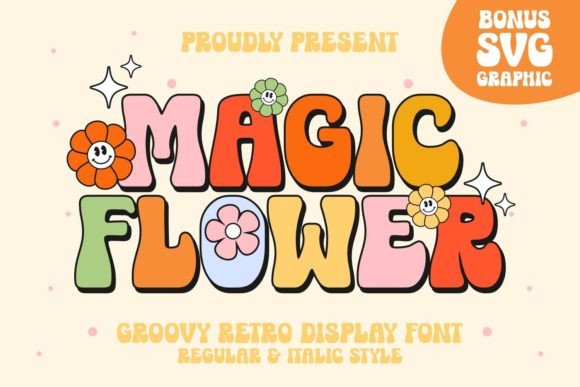
Magic Flower
Magic Flower – A Fonte Retro que Transforma Seu Design em Psicodelia
Se você está em busca de uma tipografia que capture a essência dos anos 60/70, Magic Flower é a escolha perfeita. Essa fonte display retro‑inspirada traz o espírito hippie e groovy diretamente para o seu projeto, combinando vibes flower power com um toque artesanal que faz toda a diferença.
Por que Magic Flower se destaca?
- Estilo psicodélico autêntico: As formas das letras lembram os cartazes de festivais de música, com linhas onduladas e curvas que evocam a cultura da contracultura.
- Traços grossos e finos desiguais: Essa variação cria um visual orgânico e feito à mão, adicionando personalidade e movimento ao texto.
- Versatilidade criativa: Ideal para capas de álbuns, pôsteres de eventos, branding de marcas lifestyle, convites de festas temáticas e qualquer peça que precise de um toque playful e carefree.
- Leitura atraente: Apesar do design extravagante, a fonte mantém boa legibilidade em tamanhos de destaque, garantindo que sua mensagem seja absorvida rapidamente.
Quando usar Magic Flower?
Magic Flower brilha em situações onde o objetivo é transmitir liberdade, criatividade e nostalgia. Considere-a para:
- Cartazes de festivais de música e eventos ao ar livre
- Logotipos de marcas que valorizam o estilo boho ou vintage
- Capas de livros e álbuns que celebram a cultura psicodélica
- Design de embalagens de produtos artesanais ou cosméticos naturais
- Sites de moda alternativa, arte e cultura alternativa
Com Magic Flower, você adiciona instantaneamente um ar de hippie e groovy ao seu design, sem perder a qualidade profissional. Seus traços irregulares e a energia psicodélica fazem desta fonte uma ferramenta indispensável para quem deseja criar projetos visualmente marcantes e cheios de personalidade. Experimente Magic Flower hoje e veja como ela pode transformar sua comunicação visual em pura flower power!